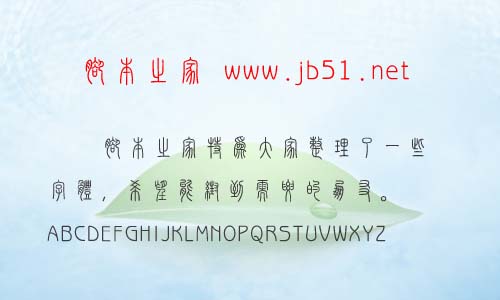
漢儀篆書繁體字體是漢儀字體庫中的一款中等粗細(xì)的篆書繁體字體,而且可以用于很多方面,比如藝術(shù)設(shè)計(jì)、書法等,喜歡的朋友們可以前來下載使用。
繁體字,亦稱繁體中文,1935年的《第一批簡體字表》稱之為正體字,歐美各國稱之為傳統(tǒng)中文(Traditional Chinese),一般是指漢字簡化運(yùn)動被簡化字所代替的漢字,有時也指漢字簡化運(yùn)動之前的整個漢字楷書、隸書書寫系統(tǒng)。繁體中文至今已有三千年以上的歷史,直到1956年前一直是各地華人中通用的中文標(biāo)準(zhǔn)字。
篆體,漢字古代書體之一,也叫篆書。是對古文字的統(tǒng)稱。“篆者,傳也,傳其物理,施之無窮。”古人認(rèn)為篆書為倉頡所造,其實(shí)是不可信的。一種文字的產(chǎn)生是要經(jīng)過一個較長的醞釀發(fā)展過程的,不可能有一個人在短時期能完成。廣義的篆體包括隸書以前的所有書體以及延屬,如金文、石鼓文、六國古文、小篆、繆篆、疊篆等。狹義主要指“大篆”和“小篆”。篆書字劃圓轉(zhuǎn),結(jié)構(gòu)依六書之義,故唐孫過庭謂:“篆尚婉而通”。